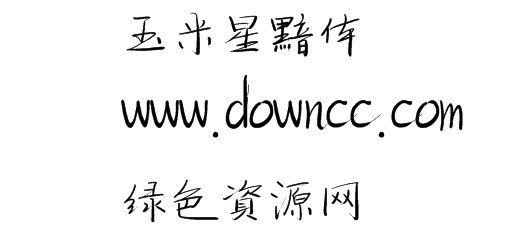
星黯體是玉米字體系列的手寫字體,字體連貫而不潦草,灑脫而不失慷慨之氣,是一款表達(dá)效果良好的pop字體,喜歡的朋友就來綠色資源網(wǎng)下載收藏吧!
星暗體字體書寫流暢,構(gòu)型簡約大方,給人十分舒適的視覺體驗(yàn),字跡明滅如同星光閃閃,可以廣泛使用在平面設(shè)計(jì)、藝術(shù)設(shè)計(jì)、海報(bào)設(shè)計(jì)等諸多領(lǐng)域!